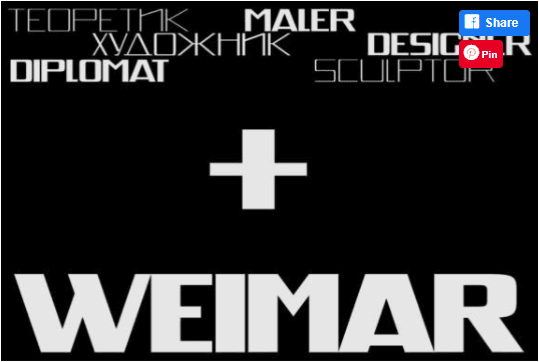
Weimar Font
Веймар вдохновлен периодами Баухауза и ВХУТЕМАСа. Игра контрастов и смелых форм букв. Подходит для плакатов, логотипов, заголовков в журналах или на веб-сайтах, а также для обложек книг. В нем есть определенная архитектурная эстетика, тектоника. Это как модернистская архитектура, переведенная в шрифт.